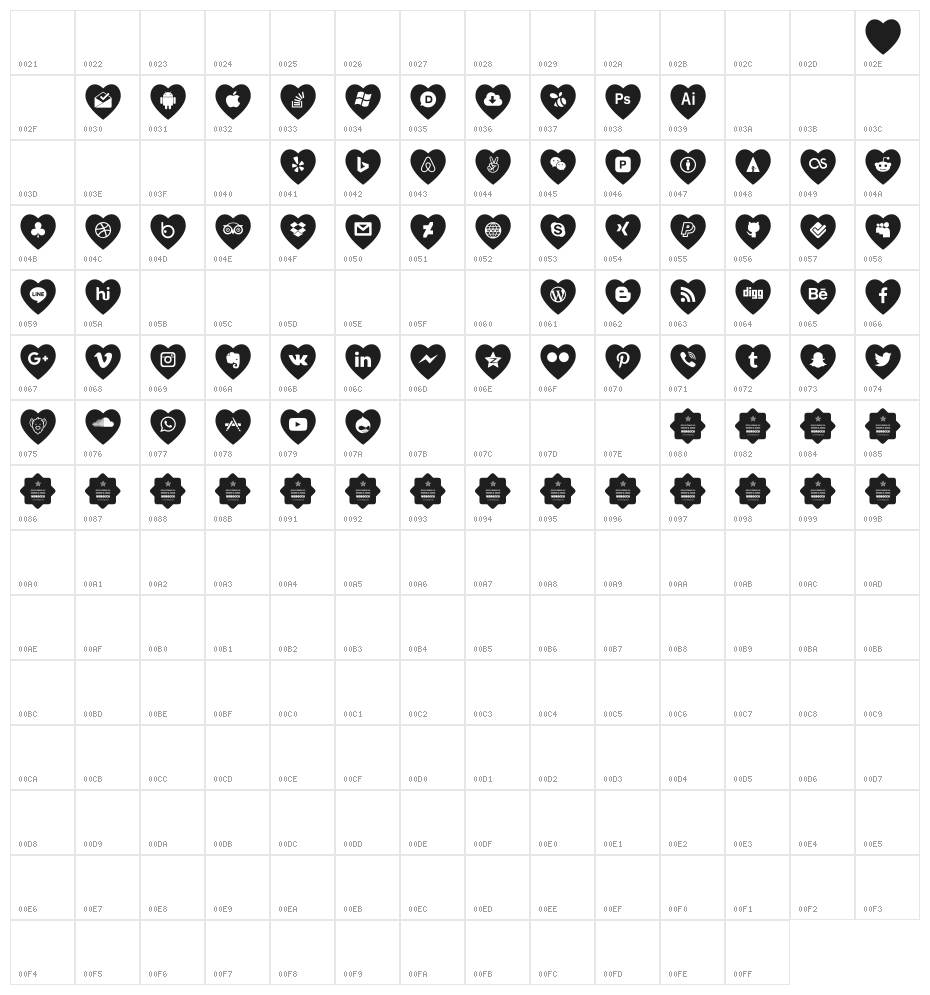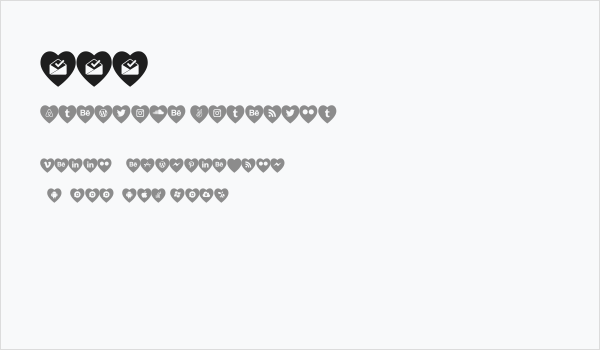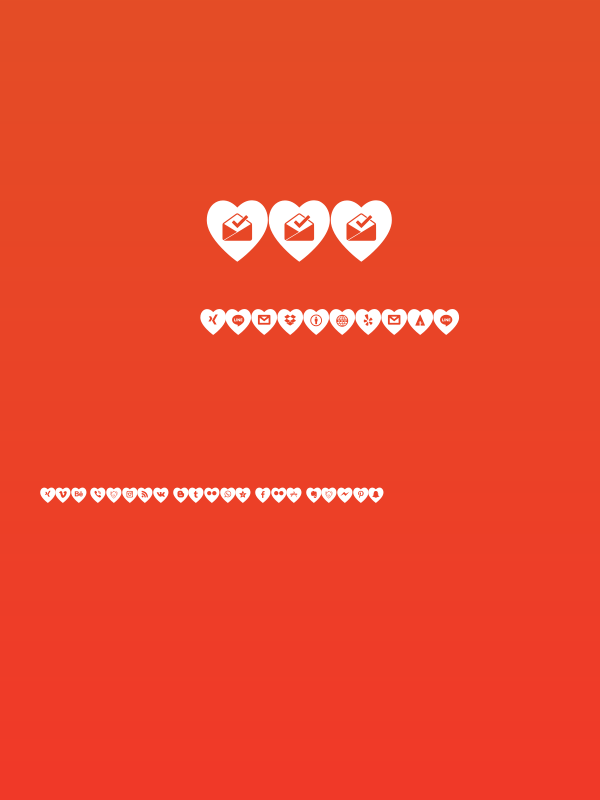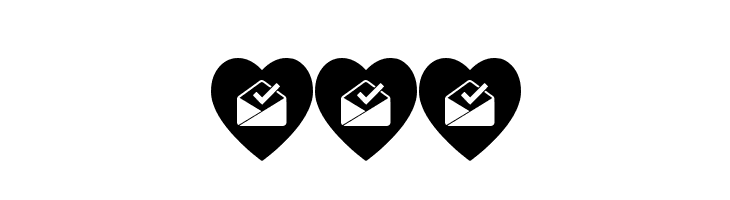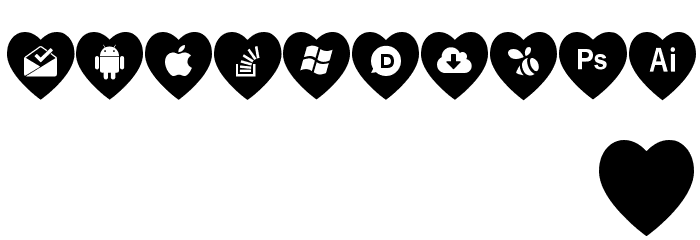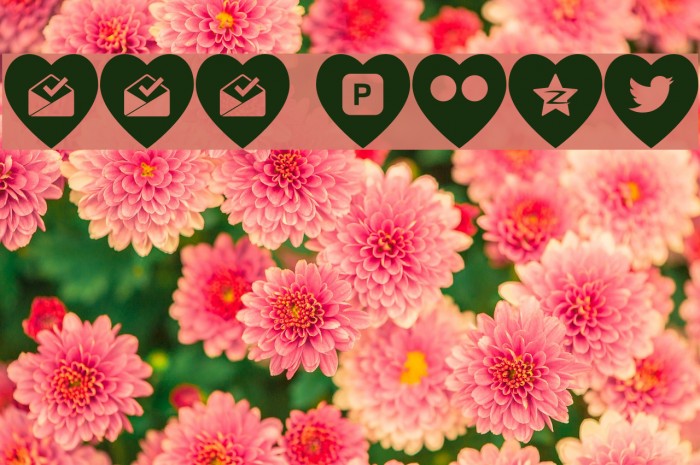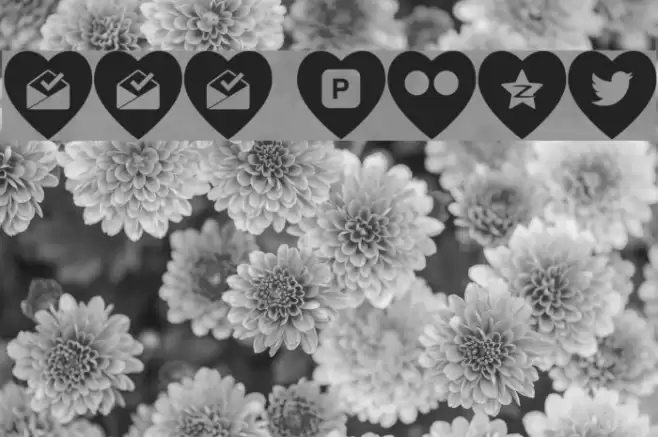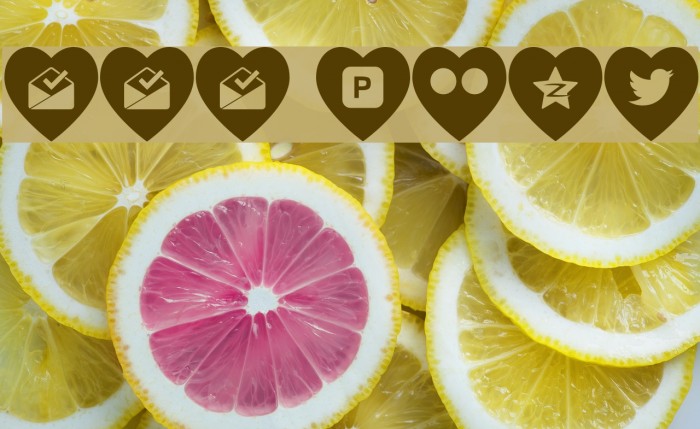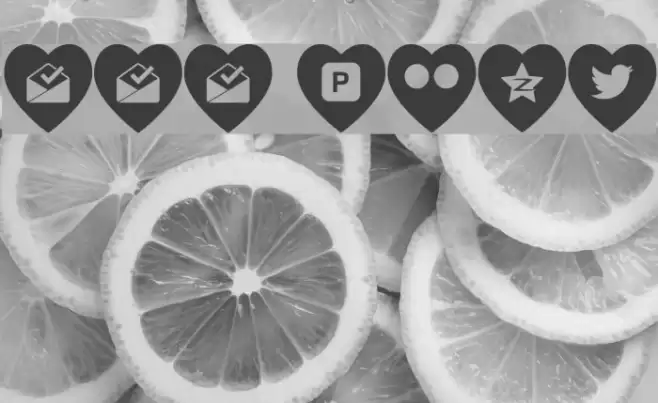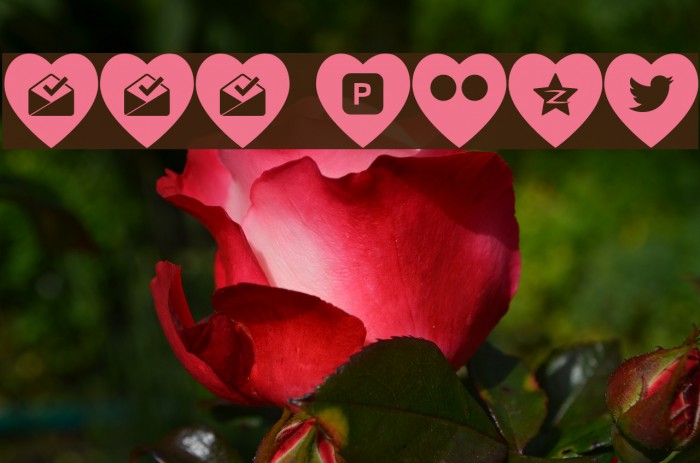
000 Font
✎ Dingbats
| 全体的なスタイル | Decorative, Modern |
| 用途 | Icons, UI elements, Themed graphics |
| おすすめプロジェクト | Social media graphics, app UI mockups, Valentine's Day tech promotions, themed icon sets. |